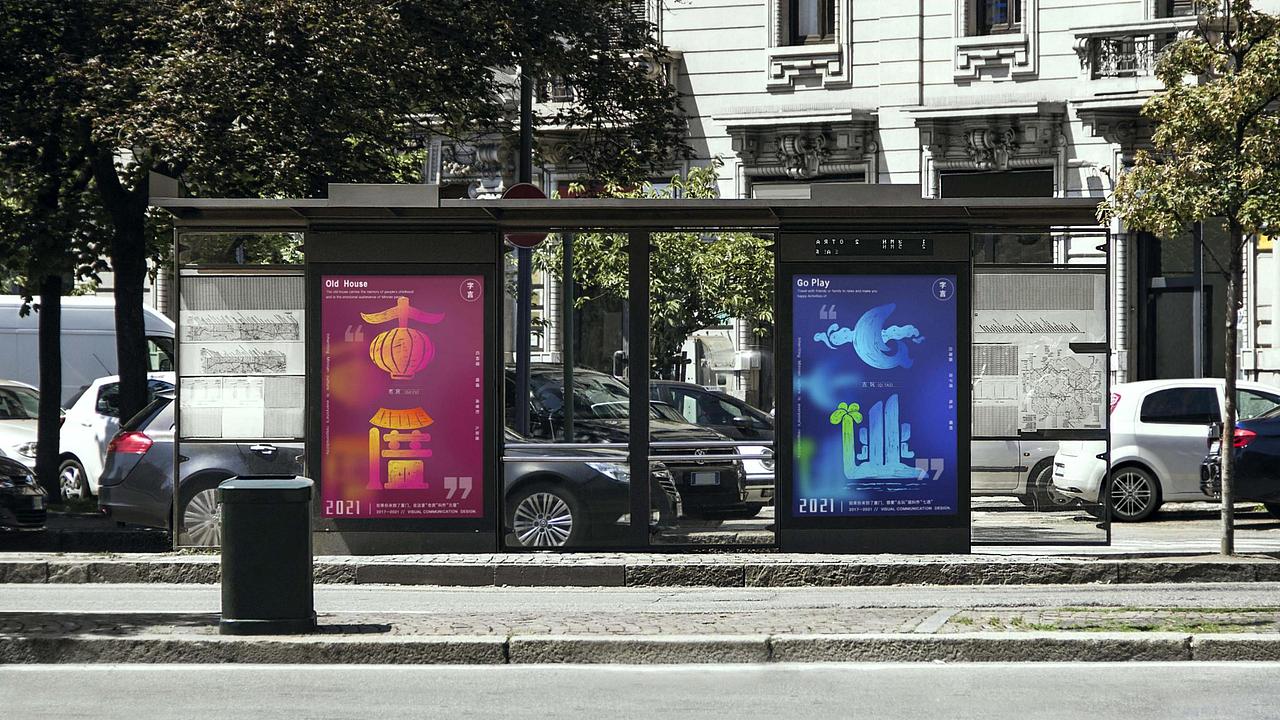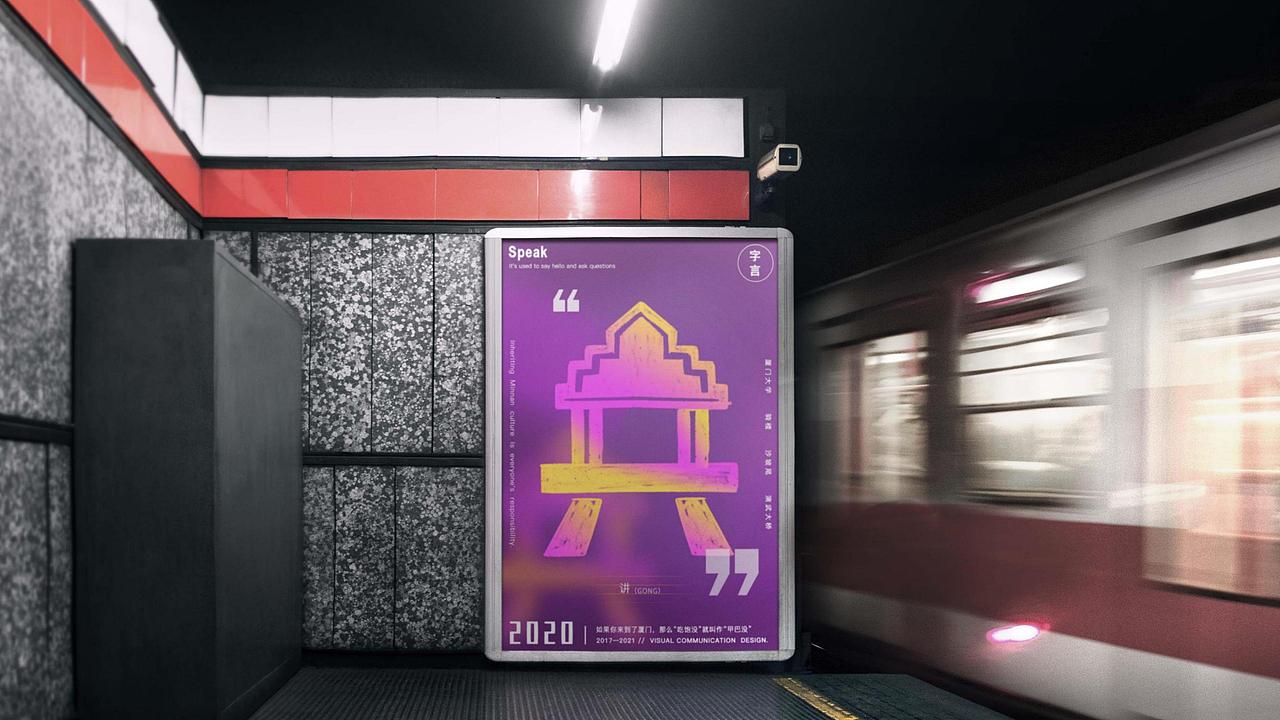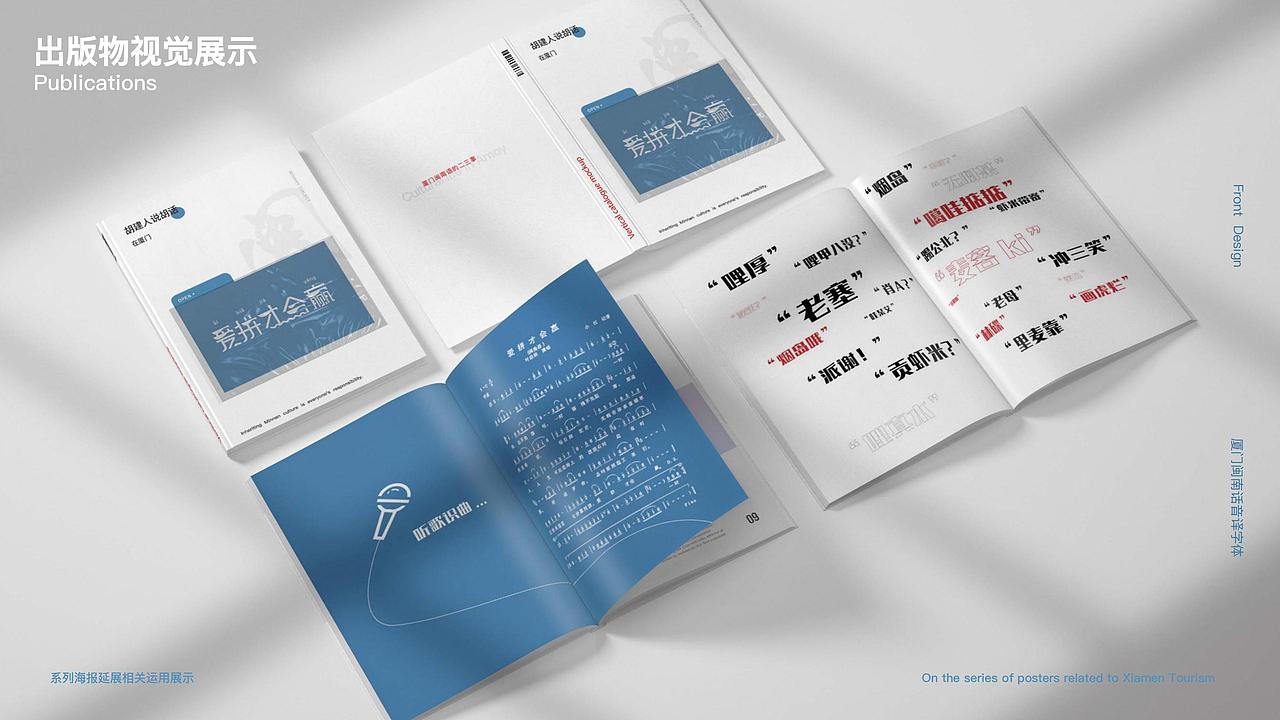
#2021青春答卷# “爱拼才会赢”闽南语字体海报
四年大学生活转瞬即逝 毕业设计如期而至
随着时代的快速发展 普通话的大力推广下
方言文化好像在社会发展中开始慢慢在淡出我们的生活
当然 我也不例外(现在回到厦门 很多时候会一瞬间想不起一些话怎么去表达了)
所以这次通过将字体与厦门元素进行融合的设计来突出厦门特色
在传播闽南语的同时能让大家有机会了解厦门
与此同时
在配色当中 我选取了厦门的代表色蓝色与闽南文化的代表色红色,以渐变的形式进行系列的设计
打破大众对闽南的刻板印象
以一种新潮的方式来表现“闽南语文化”
音译化的字体能让人们可以更为直观去解读闽南语 学习闽南语